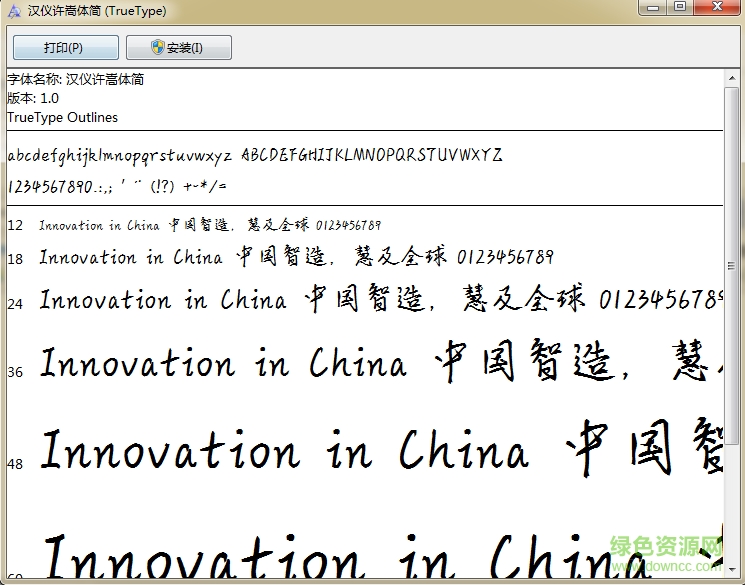
漢儀許嵩體是根據(jù)著名歌手許嵩的字跡創(chuàng)作的漢儀書(shū)法字體,喜歡VAE的朋友不要錯(cuò)過(guò)啊,綠色資源網(wǎng)為大家提供一個(gè)更接近愛(ài)豆的機(jī)會(huì)喲!
漢儀許嵩體字體介紹
音樂(lè)的靈感只在瞬間,才子的心動(dòng)盡在筆尖。